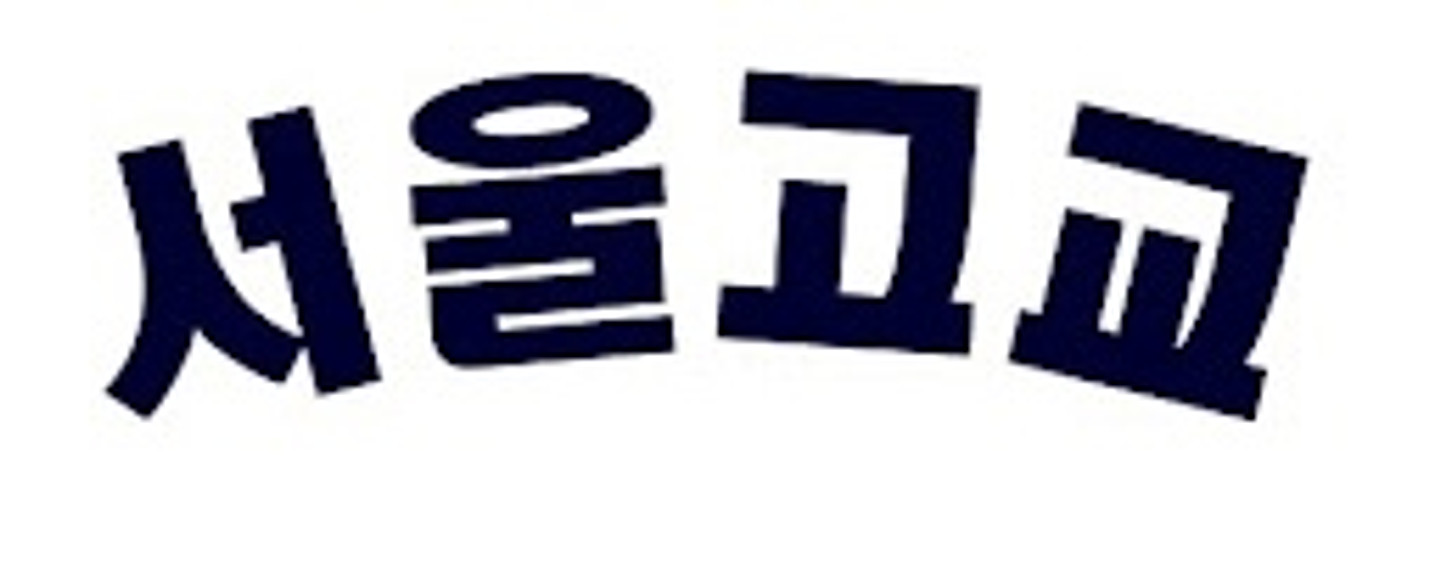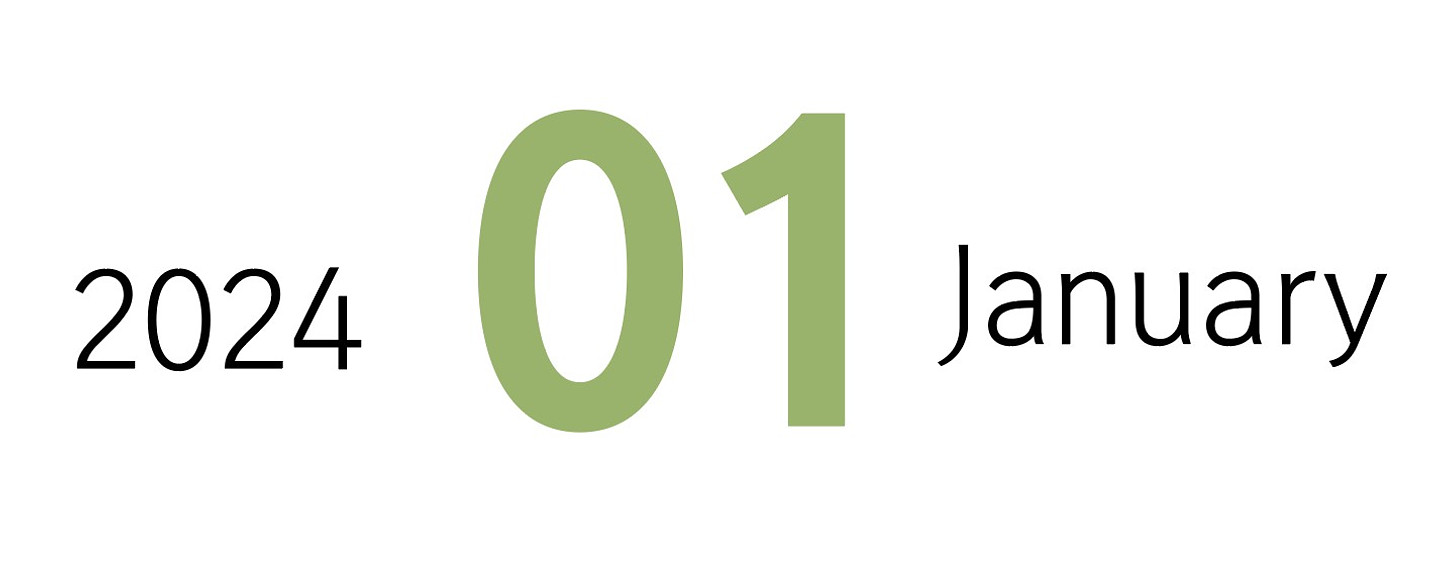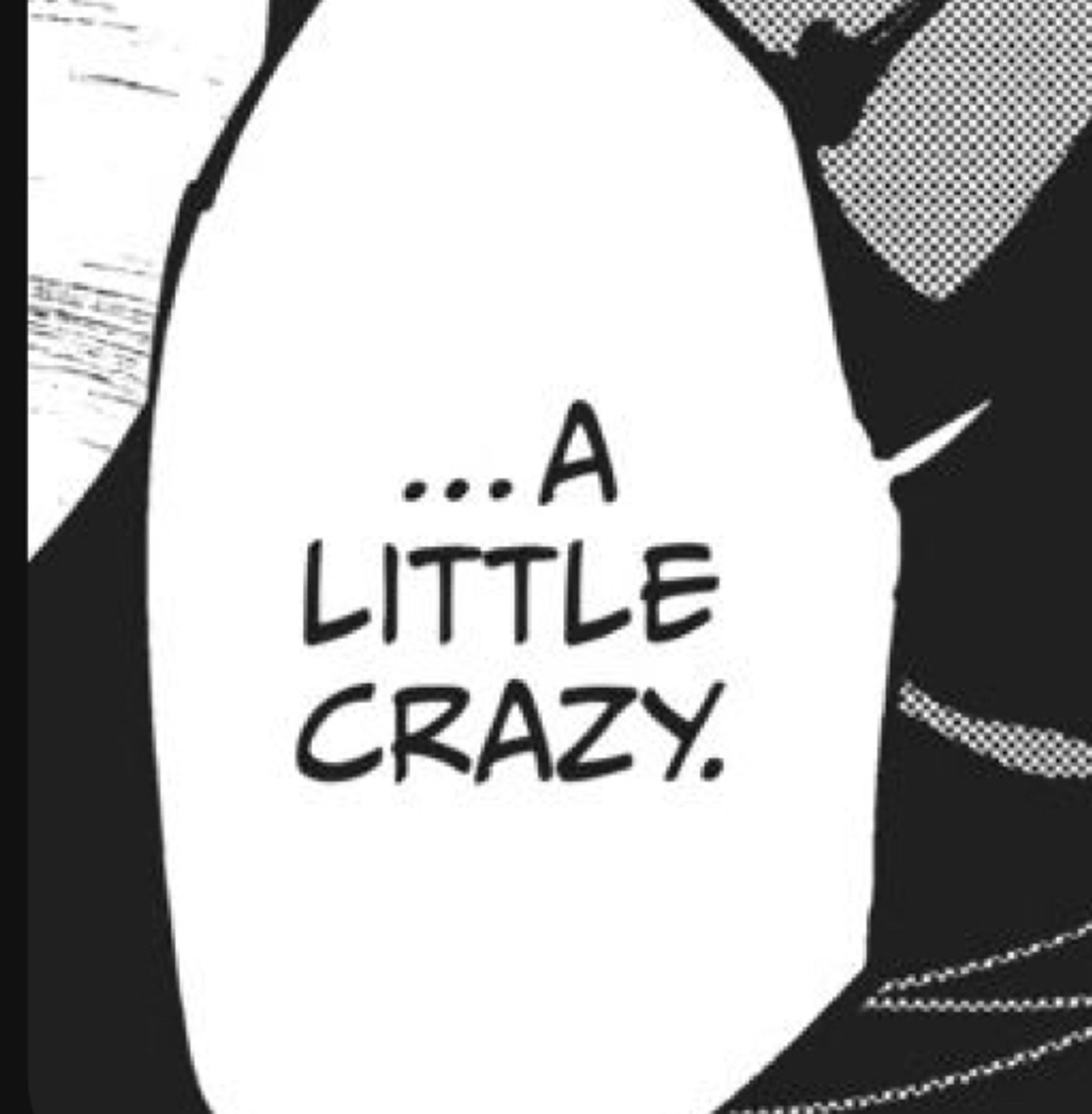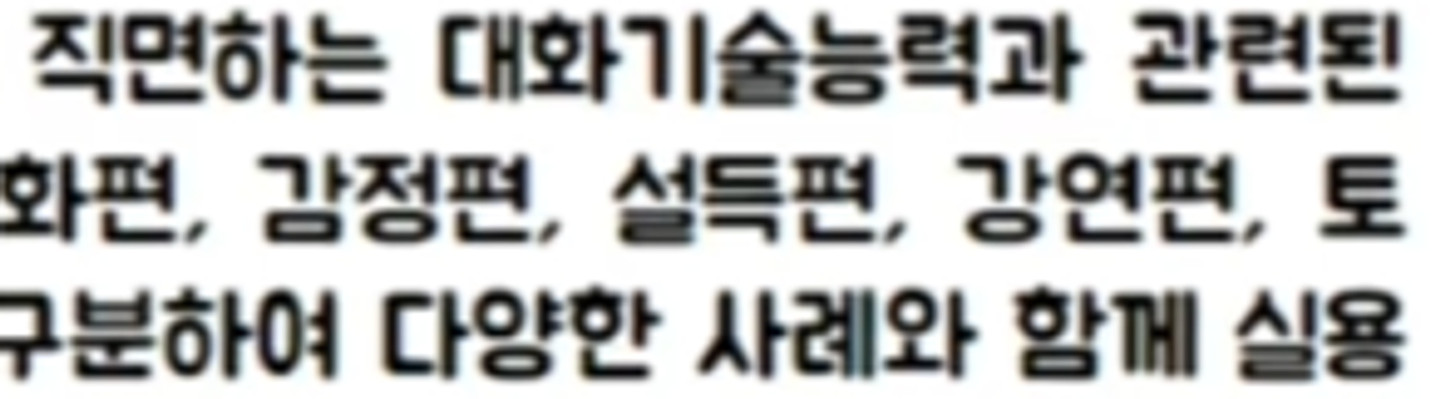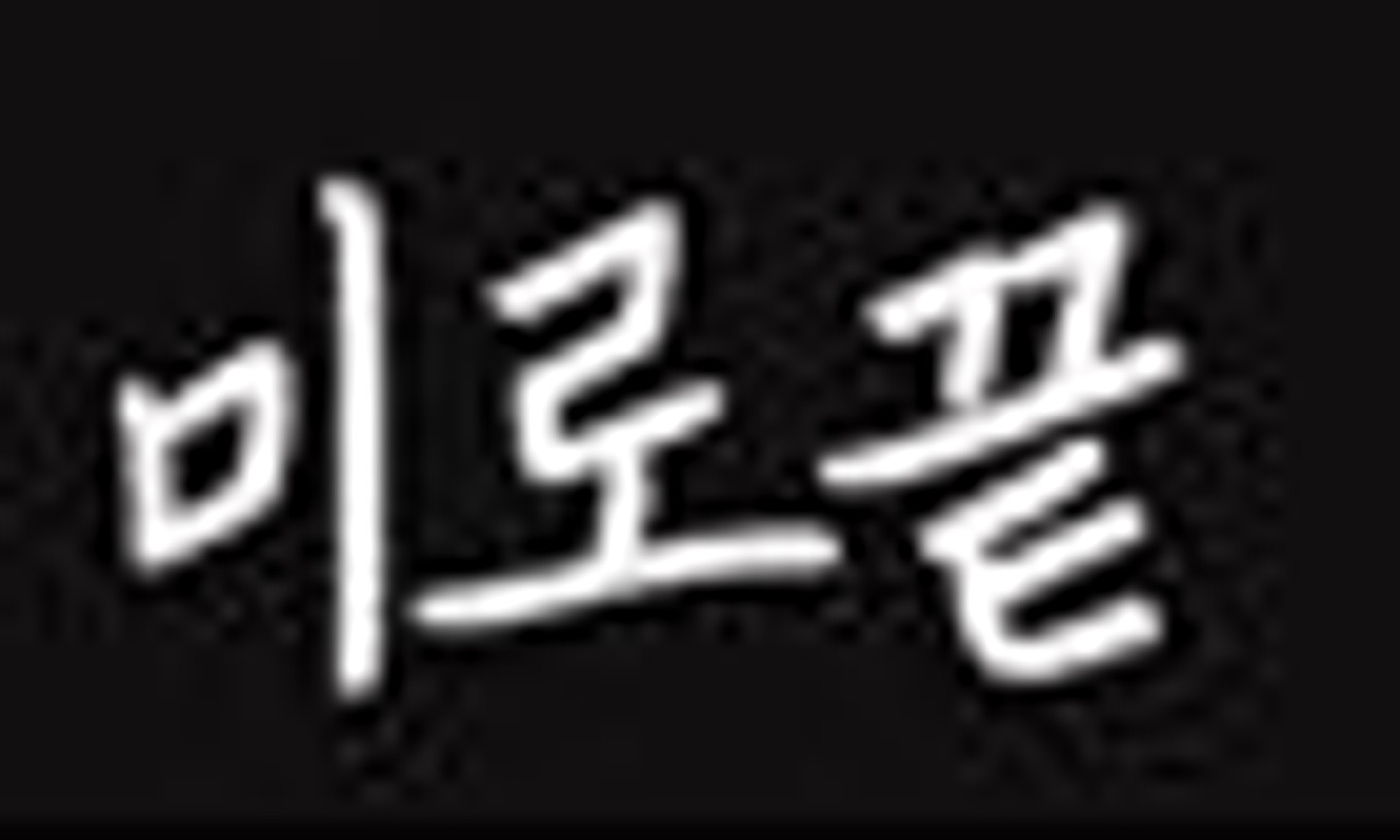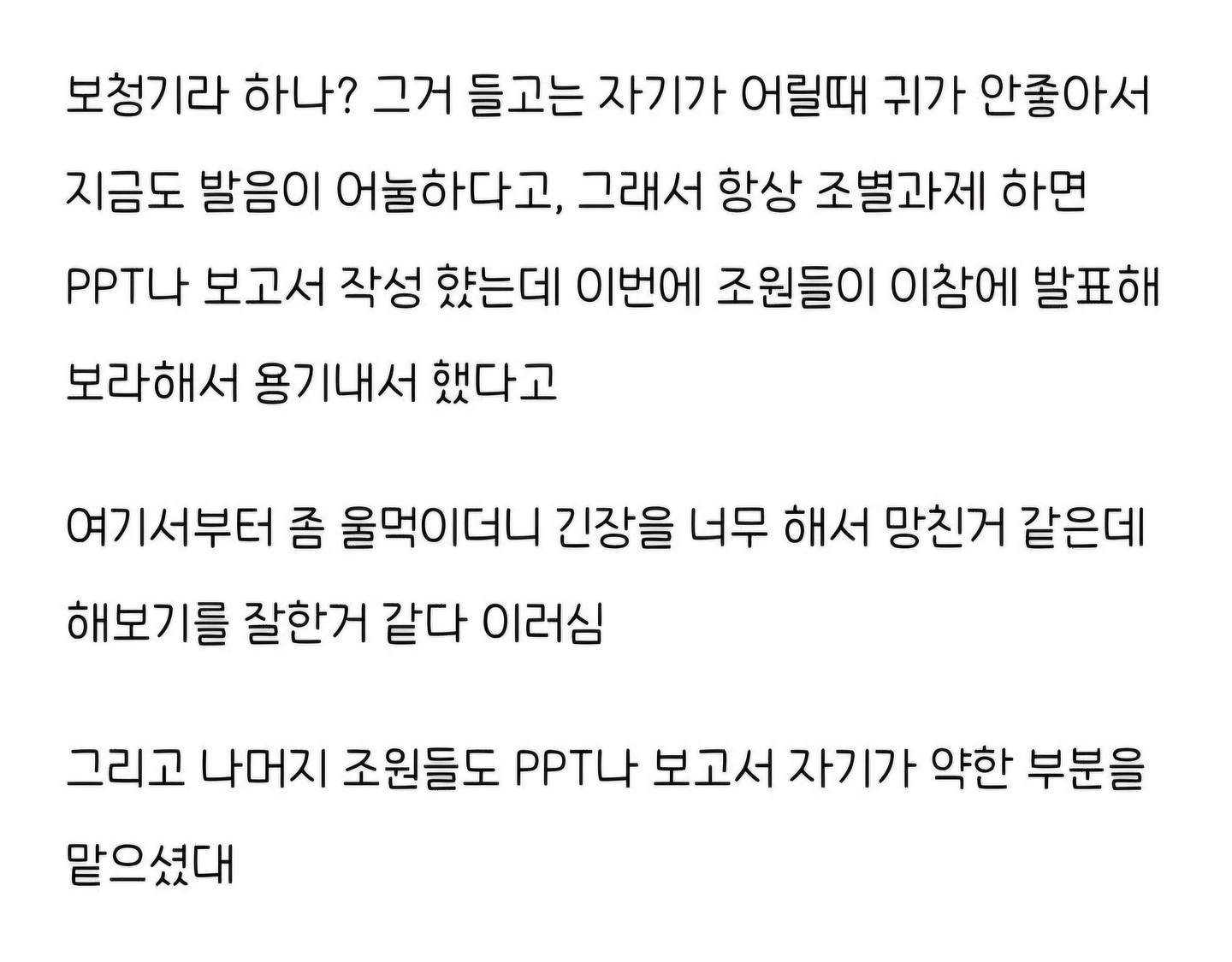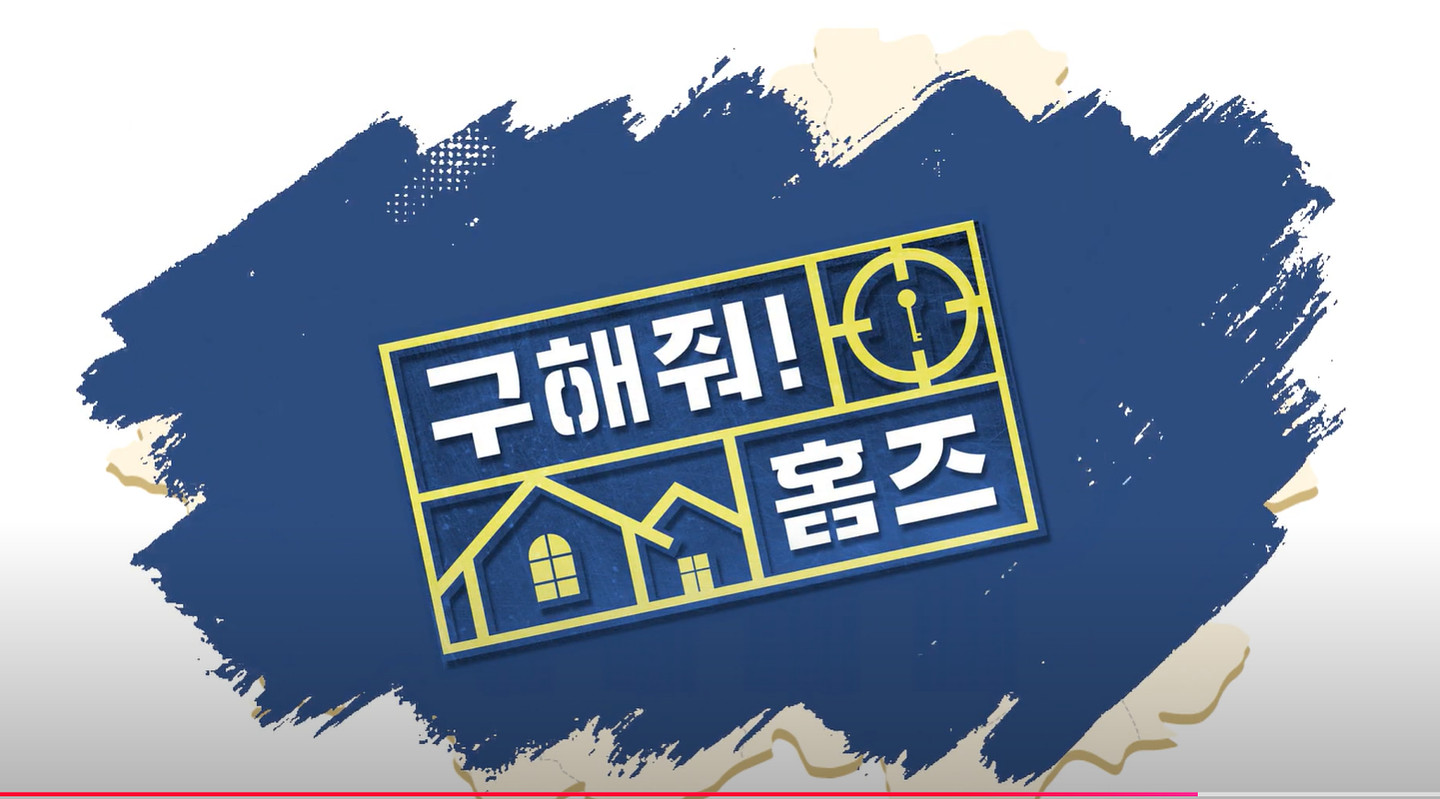
이 폰트는 무슨 폰트인가요?
해당 영상에 나온 폰트가 뭘까요? 조선 굴림체보다는 위아래 폭이 더 좁은 거 같은데...아는 분 계신가요?
왼쪽 아래에 두 폰트가 혹시 무슨 폰트일까요?
무슨 포트 인가요? 감사합니다.
무슨 폰트에요??
이 글씨체 궁금해여요 ㅠㅠㅠㅠ
폰트 알려주실분 급해요
이거 무슨 폰트인가요 급해요!!!!!!!!ㅜㅜ
이거 뭐죠??
환승연애 폰트 찾아주세요ㅜㅜ
프레젠테이슨 글씨체 뭔가요 이외다 글씨체도 알려주세혀
미지의 서울 예고편 보다가 자막이 어떤 폰트인지 궁금해졌어요..알려주세요
이 폰트의 이름을 알고싶습니다!!
한국애견연맹 핸들러 매뉴얼 본문 폰트입니다. 교과서에 쓰이는 명조체 같은 느낌인데 무슨 폰트인지 궁금합니다.
천지오의 버려진 개처럼 뮤직비디오에 있는 폰트인데 너무 예쁘네요. 어떤 폰트인지 알려주세요
이 폰트 궁금합니다~ 미리 감사합니다!!
폰트궁금해요ㅜㅜ
대체 무슨 폰트인가요???
무슨 폰트인지 궁금해요 ㅠㅠ
혹시 무슨 폰트인지 아시는부뉴ㅜㅠ 아님 비슷한 폰트라도 아신다면 알려주세요
레모나 C750 폰트
안경만두에 자주 등장하는 글씨체입니다. 무슨 폰트일까요?
세계 차 없는 날 저 폰트 어떤 폰트일까요? 둥글둥글 귀엽네요
이거 무슨 폰트인가요...
Broken 무슨폰트인가요?
글씨체 궁금합니다
무슨 폰트 인가요?ㅜㅜ
옛날폰트느낌인 이 폰트가 궁금해요
수정하려고 하는데 폰트를 알수 없어서 도움을 요청드려요~~
무슨 폰트인지
두꺼운 고딕체?
폰트 알려주세요 ㅠㅠ
이폰트에 대해서 알려주세요 부탁드립니다.
삼성왕조시절 박석민 선수 등번호 폰트인데 "18" 저 폰트는 뭔가요?
여기 나오는 한글 폰트 알려주실 수 있을까요?
유튜브에서 본 폰트인데 무슨 폰트인가요?
플래시 게임 같은 곳에서 많이 본 폰트 같은데 뭔지 모르겟어요...
폰트 이름좀 알려주세요^^
어떤 폰트인지 아시는분이요^^
이 폰트 찾아주세요!! 제발 ㅠㅠ 부탁드립니다
마커스워십 20250529 실황 영상 중 2시간 2분 40초 즈음 부분인데 저 스크린샷에 나와있는 폰트들 이름이 궁금합니다
저 N 저거 도대체 무엇이죠.... 폰트 도와주세용 ㅠ
HG키큰꼬딕인줄알았는데 살짝 다르네여 ㅠ 폰트 궁금합니다아
폰트명이 뭘까용??
요 폰트 뭘까용??
산울림 삼겹살 폰트가 궁금합니다!
이런 폰트는 무슨 폰트 인가요?
글씨체 궁금해요ㅠㅠ
무슨 폰트인지 너무너무 궁굼해요 ㅠ.ㅠ
이거 폰트 뭘까요?
에스파 비하인드 이거 폰트가 뭘까요?
이거 폰트가 뭘까요?